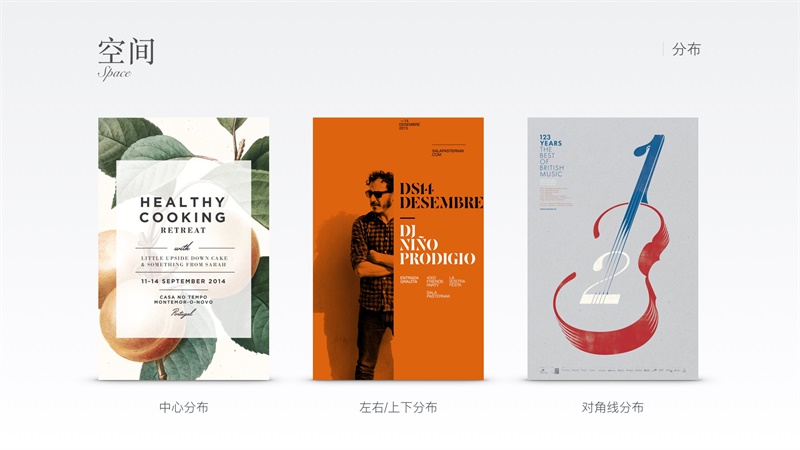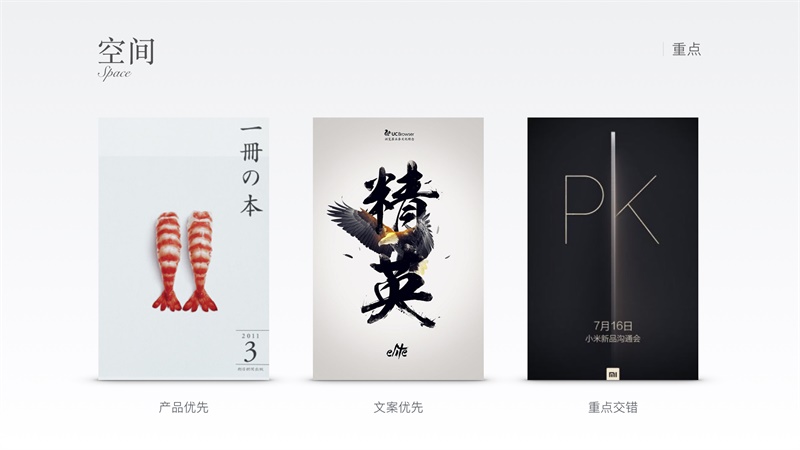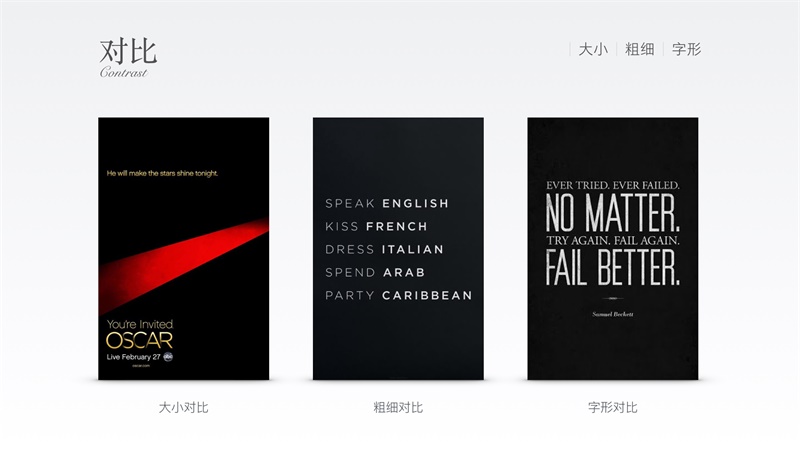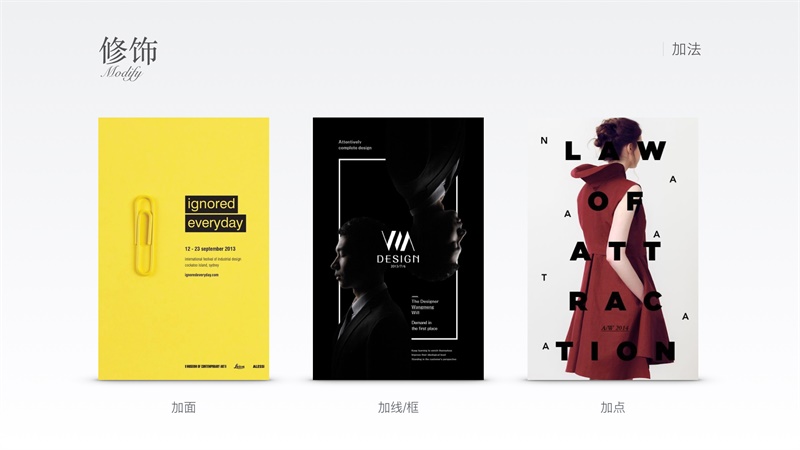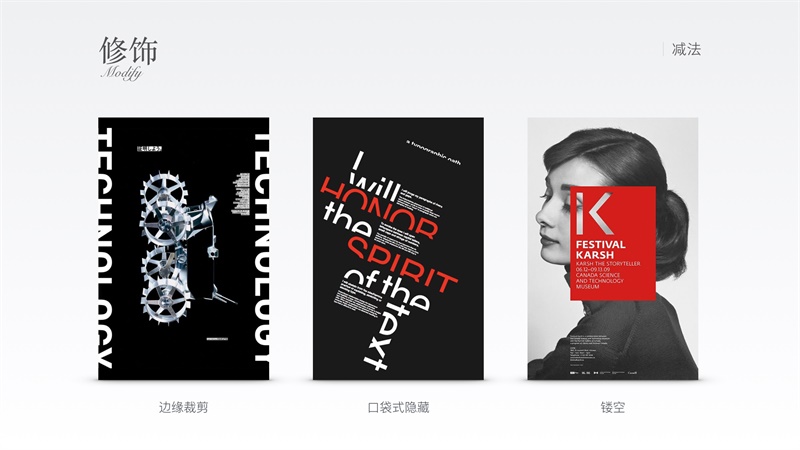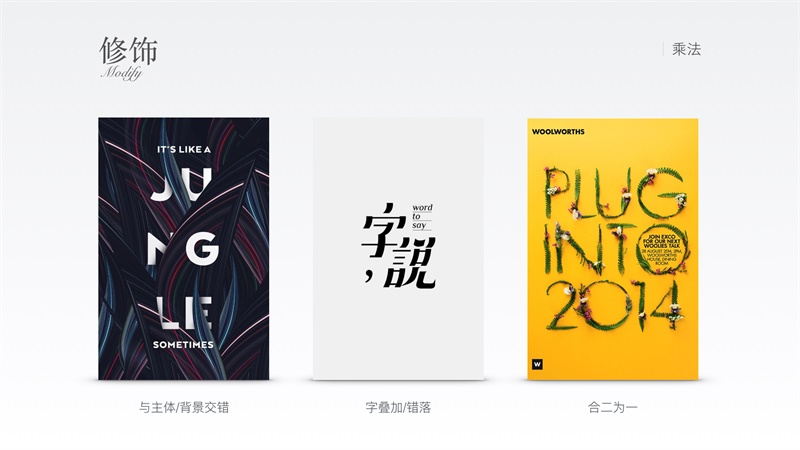
日常使用:文案字體排版
文案字數太多無從下手?甲方執迷不悟塞一堆文字?怎樣讓一坨坨文案在排版上更加高大上?莫慌。@筆戈科技 的 新葉同學基於各種優秀海報,分別從空間、對比、修飾三個方面,循序漸進,總結其文案排版方法和表現形式,最後通過實例演示,聊聊如何把這些排版技巧運用在實際設計中。
空間,就是合理地佈局文案並突出重點。在對的位置裡,遇見對的文案。
空間上的佈局,常見有三種。
中心分布:文字為主要內容,或與圖相關聯,畫面穩定。
左右/上下分布:大部分 banner 常用的分布形式,容易平衡版式,內容文案區別對應性強。
對角線分布:相對以上兩種更有視覺衝擊,不呆板,一般文案為輔助說明,可以以展示產品細節為主。
在找個好佈局安放文案的同時,還要突出該強調的重點。
圖一:產品為重點,文案為輔助(此處文案應該屬於冊集說明)。
圖二:「精英」文案為主體,以鷹來表現,增加畫面感,屬於物體服務於文案。
圖三:PK與類似鋼材材質結合,表現出宣傳重點。
對比,就是在確定文案的空間後,讓文案本身的字體產生差異,形成對比。有對比,才有傷害,才有視覺衝擊力。
大小對比:最明顯也最常用,也最容易產生效果,幾乎大部分文字排版都使用了這種方法來突出主次。
粗細對比:類似於粗密、深淺,錯落有致,從而產生視覺重心。
字形對比:相對以上兩種更加自由多樣,最普通的為襯線體與非襯線體的對比,甚至還可以進行字體設計,加入圖形元素等。
最後,修飾。可有可無,看畫面的需要。通過各種加法、減法、乘法進行修飾,可以為單調的文字加上一些細膩的細節。
修飾上的加法:在基礎文案上添加元素,加強重點,平衡版式。
加面:以面狀出現在文案字體中的,一般作用於重點文案,或者是需要吸引點擊的按鈕,和框選區分內容。
加線:修飾文字,引導文字,整理文字,平衡畫面等。
加點:可以跟主體搭配,充盈畫面。
修飾上的減法:在文案的表現形式中做出裁剪,隱藏或者鏤空。
邊緣裁剪:擴大空間感,在一些日式設計中,有時會故意放大字體到邊緣撐住版面。
口袋式隱藏:隱藏看得懂,修飾文字的同時還能引發想象。
鏤空:除了可以強調重點文案或主體外,還可以疊加肌理、材質效果於鏤空部分。
修飾上的乘法:通過交集產生特殊效果。
與主體/背景交錯:交錯式,更有前後空間感,與圖片主題內容上有更多交互。
字疊加/錯落: 突破呆板的的橫竪直排方法,悅動。
合二為一:技術上要求比較高,主體物和文案相容,表達更為直接。
接下來我們通過具體案例來進行實際操作。
以7.8號全球上映的大魚海棠為例,僅對文案排版進行研究,暫不涉及圖片哦。
借用大魚海棠毛筆字體作為主體來進行設計:
圖1:中心排版,文案的大小對比,毛筆字和宋體的字形對比,最後用引線作為英文文案的引導。
圖2:上下排版,主體放在中間,並用線框包圍,毛筆字突破邊界。
圖3:對角線排版,並用紅線平衡畫面重心。
接下來我們「大魚海棠」為重點,僅使用普通的字體來進行排版。
圖1:塊狀分布,對齊後更加整潔,利用修飾線以區分層次。
圖2:加面,點,粗細等修飾。
圖3:乘法上的字間錯落。